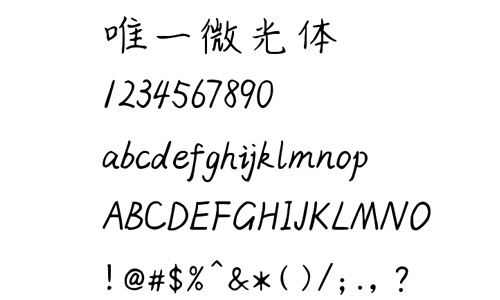
唯一微光體字體是思雨字庫中一款非常不錯的硬筆手寫字體, 薔薇盛放的年華盡端,你微笑的剪影,是守望靜謐的唯一微光。——唯一微光體。本字體是在國家標(biāo)準(zhǔn)簡體字庫GB2312所包含6763漢字的基礎(chǔ)上,又增加了近200常用字,已經(jīng)覆蓋了大陸99.75%的漢字使用頻率,足以滿足日常需求。歡迎大家前來下載。